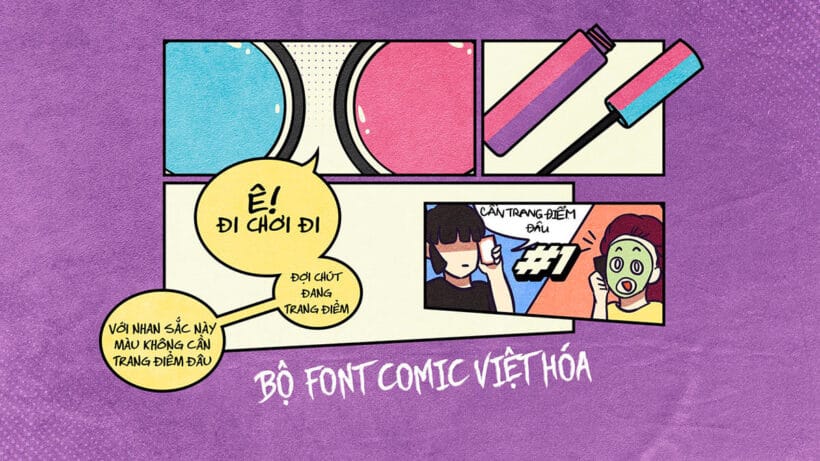
Tổng hợp font chữ truyện tranh Comic Việt Hóa siêu đỉnh
Bạn yêu thích truyện tranh? Hay bạn là người tạo ra các tác phẩm truyện tranh, nhưng đang đau đầu vì chưa tìm được font chữ chuẩn chỉnh, đẹp và đậm chất comic? Đừng lo, bộ sưu tập 76 font trong bộ Comicraft & Blambot Việt hóa chính là “vị cứu tinh” mà bạn đang tìm kiếm!
Được Việt hóa bởi Johan the Laurant, một cái tên quen thuộc trong giới sáng tạo thuộc DCVN & Hội Comic Phương Tây, bộ font này không chỉ đẹp mà còn đầy đủ các yếu tố cần thiết cho một tác phẩm truyện tranh chuyên nghiệp.
Comicraft & Blambot là ai mà ghê gớm vậy?
Nếu bạn là fan của các siêu anh hùng, chắc chắn bạn đã từng thấy font chữ của họ! Comicraft và Blambot là hai thương hiệu hàng đầu chuyên thiết kế font chữ dành riêng cho truyện tranh. Từ Marvel, DC Comics cho đến vô số tác phẩm độc lập, những font chữ này đã “tỏa sáng” trong hàng ngàn trang truyện.
Và giờ đây, bộ font này đã được Việt hóa hoàn chỉnh, sẵn sàng phục vụ cộng đồng sáng tạo Việt Nam!
Điểm đặc biệt của bộ font Comicraft & Blambot Việt hóa
Phù hợp với mọi nhu cầu truyện tranh: Bộ font này bao gồm tất cả các kiểu chữ bạn cần để tạo ra một trang truyện hoàn chỉnh: từ font lời thoại, font hiệu ứng âm thanh (như “BOOM!”, “WHAM!”), font tiêu đề, đến font mô tả.
Tính nghệ thuật cao: Các font đều được thiết kế với phong cách đặc trưng của truyện tranh Mỹ: năng động, vui nhộn, đôi khi đầy kịch tính. Dù bạn viết về siêu anh hùng, ma quái, phiêu lưu hay hài hước, bộ font này đều có thể cân tất.
Việt hóa chuẩn không cần chỉnh: Bạn đã bao giờ gặp tình trạng font đẹp nhưng không hỗ trợ tiếng Việt? Với bộ font này, bạn không cần lo lắng. Dấu câu, chữ “Ư”, “Ă”, “Đ” đều được tinh chỉnh một cách hoàn hảo, đảm bảo mọi thứ mượt mà khi sử dụng.
Sản phẩm từ người đam mê dành cho người đam mê: Johan the Laurant và cộng đồng DCVN & Hội Comic Phương Tây đã dành rất nhiều tâm huyết để Việt hóa bộ font này. Điều đó có nghĩa là bạn đang sử dụng một sản phẩm được chăm chút bởi những người thực sự hiểu và yêu truyện tranh.
Vì sao bạn nên sở hữu ngay bộ font này?
Nâng tầm tác phẩm truyện tranh: Một font chữ đúng chất sẽ khiến tác phẩm của bạn trông chuyên nghiệp hơn rất nhiều.
Tiết kiệm thời gian: Không còn mất công tìm kiếm font hỗ trợ tiếng Việt phù hợp. Tất cả đã có trong một bộ duy nhất!
Khả năng ứng dụng cao: Ngoài truyện tranh, bạn còn có thể sử dụng bộ font này cho poster, banner, thiết kế quảng cáo, hoặc thậm chí là… thiệp mời sinh nhật với phong cách siêu anh hùng!
Một vài “anh tài” nổi bật trong bộ 76 font
• Comicraft Regular: Font chuẩn chỉnh cho lời thoại nhân vật.
• Pow Comic: Hoàn hảo cho tiêu đề hoặc biểu cảm mạnh mẽ.
• Scream FX: Font dành cho những tiếng hét ám ảnh.
Tổng kết
Hãy tưởng tượng truyện tranh mà không có font chữ đẹp thì giống như… Batman ra đường mà quên đeo mặt nạ vậy! Bộ font Comicraft & Blambot Việt hóa chính là “vũ khí bí mật” giúp bạn tạo ra những trang truyện đỉnh cao, cuốn hút từ cái nhìn đầu tiên.
Đây là danh sách 76 font trong bộ Comicraft Blambot Font Việt Hóa
1. Always Angry BB (Regular – Italic – Bold – Bold Italic)
2. Armored Science BB (Regular – Italic)
3. CC Achtung Baby
4. CC Adam Kubert (Regular – Italic – Bold Italic)
5. CC A Likely Story (Light – Light Italic – Regular – Italic – Bold Italic – Heavy Italic)
6. CC Atomic Wedgie (Regular)
7. CC Clobberin Time (Crunchy – Smooth)
8. CC Comicraft (Regular – Italic)
9. CC Comicrazy (Regular – Italic – Bold Italic)
10. CC Credit Crunch (Soft)
11. CC Cutthroat (Regular – Italic – Bold Italic – Mideval)
12. CC Dave Gibbons (Regular – Italic – Bold Italic)
13. CC Dave Gibbons Journal (Regular – Italic)
14. CC Designer Genes (Zipangu)
15. CC Dreamland (Regular – Bold Italic – Display)
16. CC Dreamland Lower (Regular – Italic – Bold Italic)
17. CC Drop Case (Solid Italic)
18. CC Dusk Till Dawn (Buried)
19. CC Elephantmen (Regular – Italic – Aged Italic – Tall Regular – Tall Italic – Greatest Regular – Tallest Regular)
20. CC Face Front (Regular – Italic – Bold Italic)
21. CC Flame On (Regular)
22. CC Grimly Fiendish (Regular – Bold)
23. CC Hammer Horror (Regular – Bold)
24. CC Hip Flask Bevel (Regular)
25. CC Hush Hush (Regular – Italic – Bold Italic)
26. CC Jeff Campbell (Regular – Italic – Bold Italic)
27. CC Joe Kubert (Regular – Italic – Bold Italic)
28. CC Kiss And Tell (Regular – Italic – Bold Italic)
29. CC Letterbot (Regular – Bold)
Demo một số font sử dụng edit comic: